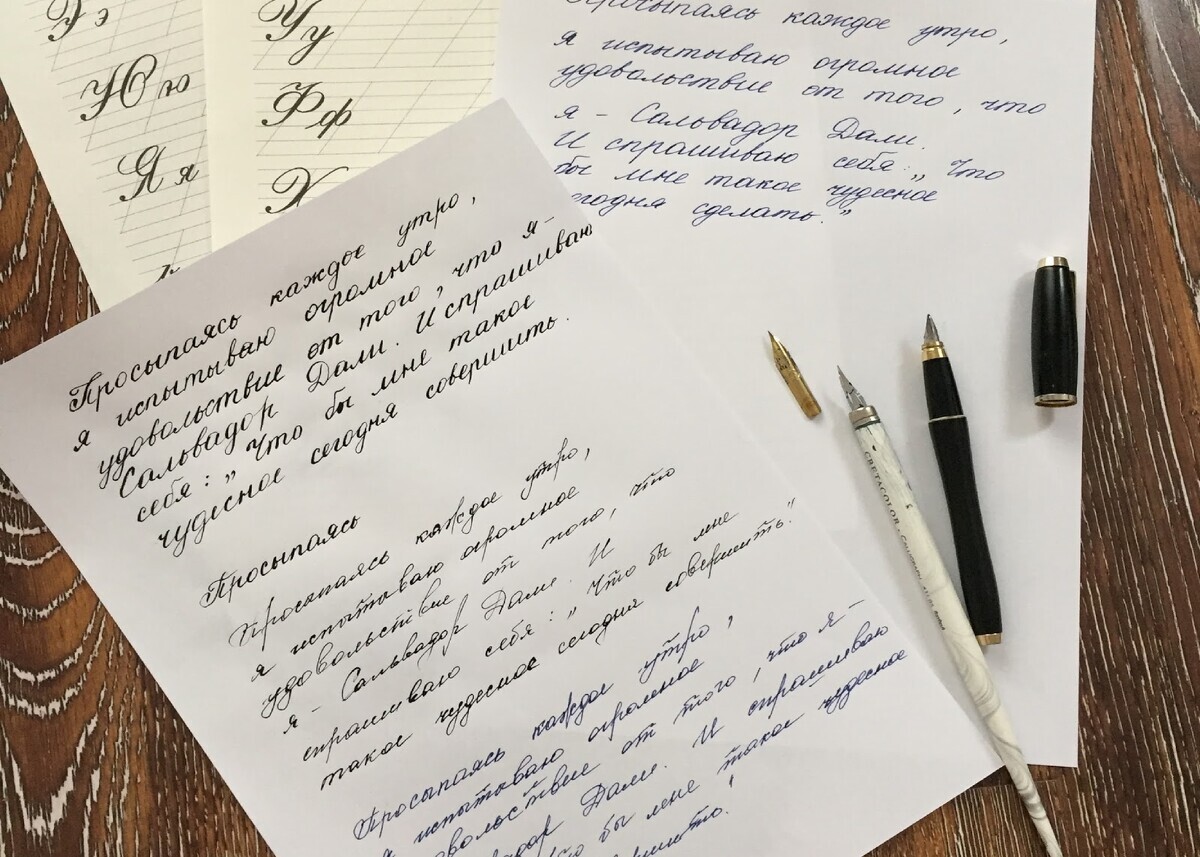
Для начала разделим эти понятия. И увидим разницу между ними.
Подход
Есть обычный школьный подход к письму - вариант «садись и пиши», когда мы идем обычным путем через прописи, тренируем навык за счет объема и механического повторения действий. К сожалению, этот метод не работает практически ни с кем. И для большинства детей письмо становится испытанием.
Есть второй вариант- проект "Игра в каллиграфию", где мы начинаем изучение мира письма, исследуя его целиком, а не один только почерк натаскиваем.
В курсе мы не пишем в стандартных прописях. Нет таких заданий, где обязательно нужно это делать. Но дети все равно в них тренируются, только без напряжения, тк относятся к прописи в черновиках как к части процесса.
Игра в каллиграфию проходит через творчество, через свободу и через возможности, которые открывают нестандартный взгляд на мир в целом.
Примите это сами и покажите ребенку, что есть множество вариантов написания и огромное количество шрифтов.
Многообразие шрифтов
Важно показать детям разницу в исполнении и применении.
1) школьный шрифт - это просто один из вариантов шрифтов. Да, мы используем его чаще всего. Но он только один из многих.
Школьный - для прописей и тетрадей,
2) рукописный кистью (с него мы начинаем обучение игре ы каллиграфию) - для письма на холстах и творческих работ.
Это нормально. У каждого своя зона использования!
В мире для каждого направления существуют свой шрифт.
Есть шрифт копперплейт, идеален для открыток и красивых тонких надписей.
Вы увидите, что кроме школьного, который постоянно используем, есть еще много другого.
Вот этим и занимаемся в игре в каллиграфию. Показываем возможности, и раскрываем собственное сознание шире. И каждый родитель находит у ребёнка свой интерес к письму. Отсюда выстраивается индивидуальная траектория обучения. ⠀
И самое главное отличие
Мы работаем на перспективу, а не на сиюминутные результаты.
Мне не важен результат прямо сейчас, прямо сегодня. Невозможно, даже 6-7 летнего ребенка за 3 дня натренировать так, чтобы писал красиво. Письмо и обучение ему это процесс, это путь, который мы проходим от первоичного интереса до мастерства. Он длинный и наполненный различными ситуациями и радости и преодоления.
Основной момент в том, что мы идем через творчество, через детские интересы, через то, что они любят, через реальные детсвие смыслы. И само собой в них происходит включение в сам процесс, и он становится важным.